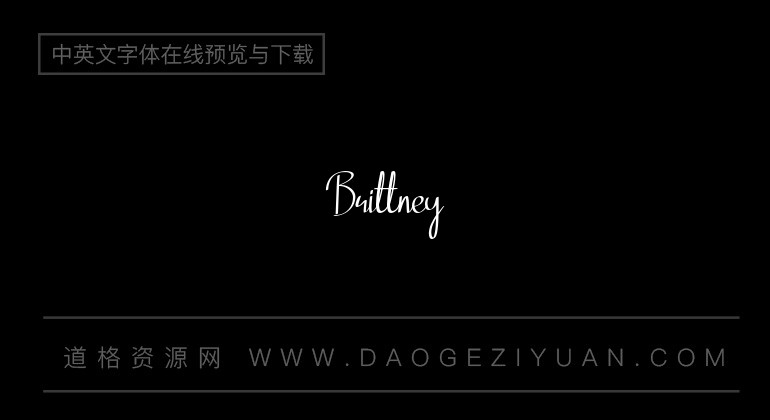
Brittney
Brittney 字体是一种优美、流畅、优雅的手写风格字体,由 Emily Spadoni 设计。该字体包含大写和小写字母、标点符号和数字,可用于许多文本设计项目,如卡片、海报、标志、包装和网站设计。Brittney 字体具有舒适的视觉效果和轻松的阅读体验,也可用于打印和数字文档。这种字体被许多设计师和创意工作者广泛应用,因为它为项目注入了一种个性化的手写风格。
Brittney是一款非常不错的手写艺术字体,具有很好的视觉感,适合于文化类的宣传设计、商业类品牌的广告和产品包装设计以及个性化文字排版等较多场景。